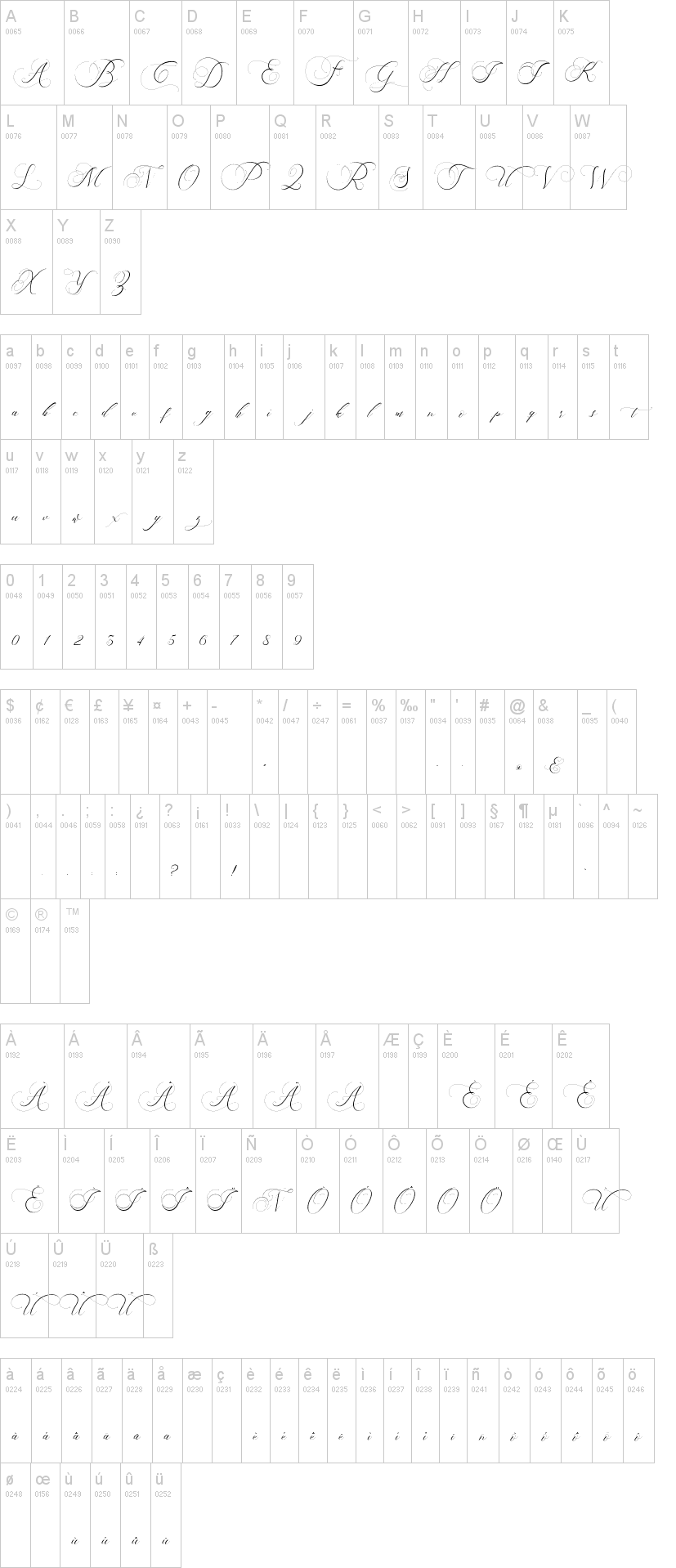
Beauty Angelique
? Beauty Angelique 字体是一款精美的花体字体,由著名的荷兰设计师 Angelique van den Berg 创作。它采用精细的线条,拥有细腻的细节和优雅的外观,让人们感受到浪漫的气息。它适用于各种印刷品、报纸和网站上的文字,可以为您的作品增添一份浪漫的气息。
Beauty Angelique是一款非常不错的手写艺术字体,具有很好的视觉感,适合于文化类的宣传设计、商业类品牌的广告和产品包装设计以及个性化文字排版等较多场景。